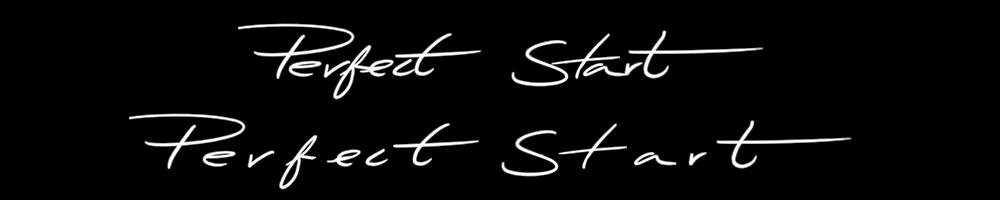
verzweifelte Suche (Perfect Start)
habe mich gerade mit der Hoffnung auf Hilfe hier angemeldet, denn ich versuche schon eine ganze weile diesen Font (s. Anhang) zu finden.
Die beiden unterschiedlichen "e" und die drei unterschiedlichen "t" lassen eher Handschriftliches vermuten, ein Font wird das nicht ein.